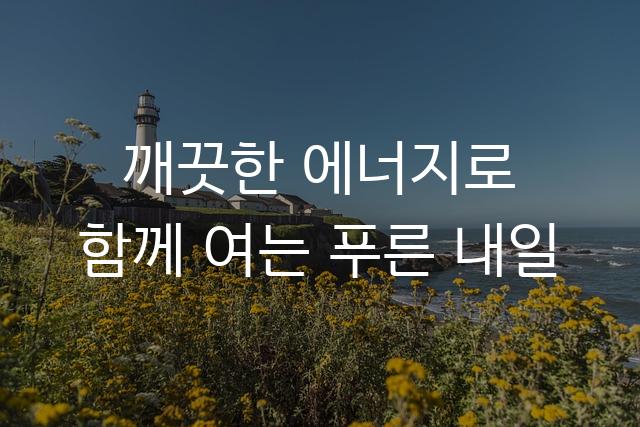
한수원 한돋움체는 제목용으로 적합한 둥근 고딕 스타일의 폰트입니다. 장식적인 요소와 굴림체의 부드러운 곡선이 조화롭게 어우러져 감각적인 디자인을 완성합니다.
한수원 한돋움체은(는)
별모양/패턴, 길고/크고, 기본 고딕, 복실복실, 부드러움, 감성적인, 장식 스타일, 둥근 스타일 계열의 생김새를 가지고 있으며
웹/앱 디자인, 출판물 제목, 보고서/문서 등에서 자주 활용되며, 효과적인 메시지 전달에 적합합니다.
이 폰트는 기술/IT, 공공/정부, 환경/에너지 분야에 잘 어울리며,
단순한, 전문적인, 신뢰감 느낌을 담고 있는 것이 특징입니다.